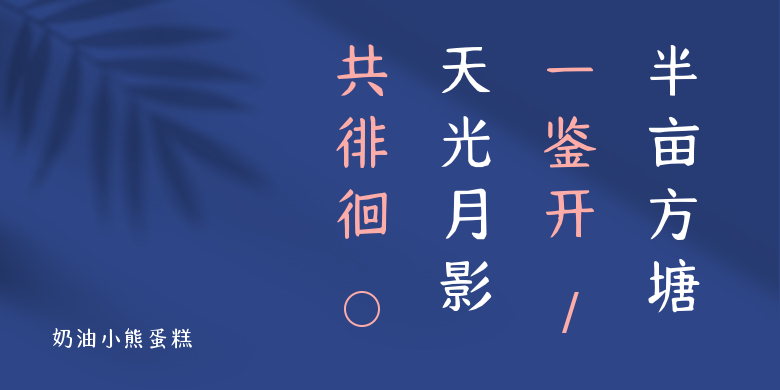
奶油小熊蛋糕
奶油小熊蛋糕,这款字体结构工整、笔画清晰,兼顾美观与易读性,适用于标题、正文、海报、包装、LOGO 等多种场景。字形优雅稳定,风格百搭耐看,适配日常排版与创意设计,让文字呈现更舒适、更具质感。奶油小熊蛋糕一笔一画,皆是细节,以均衡的比例、流畅的线条打造舒适视觉体验,字形端正大气,风格简约现代。无论是商业设计、品牌宣传还是日常排版,都能轻松驾驭,让文字更有格调与力量。奶油小熊蛋糕字体下载。